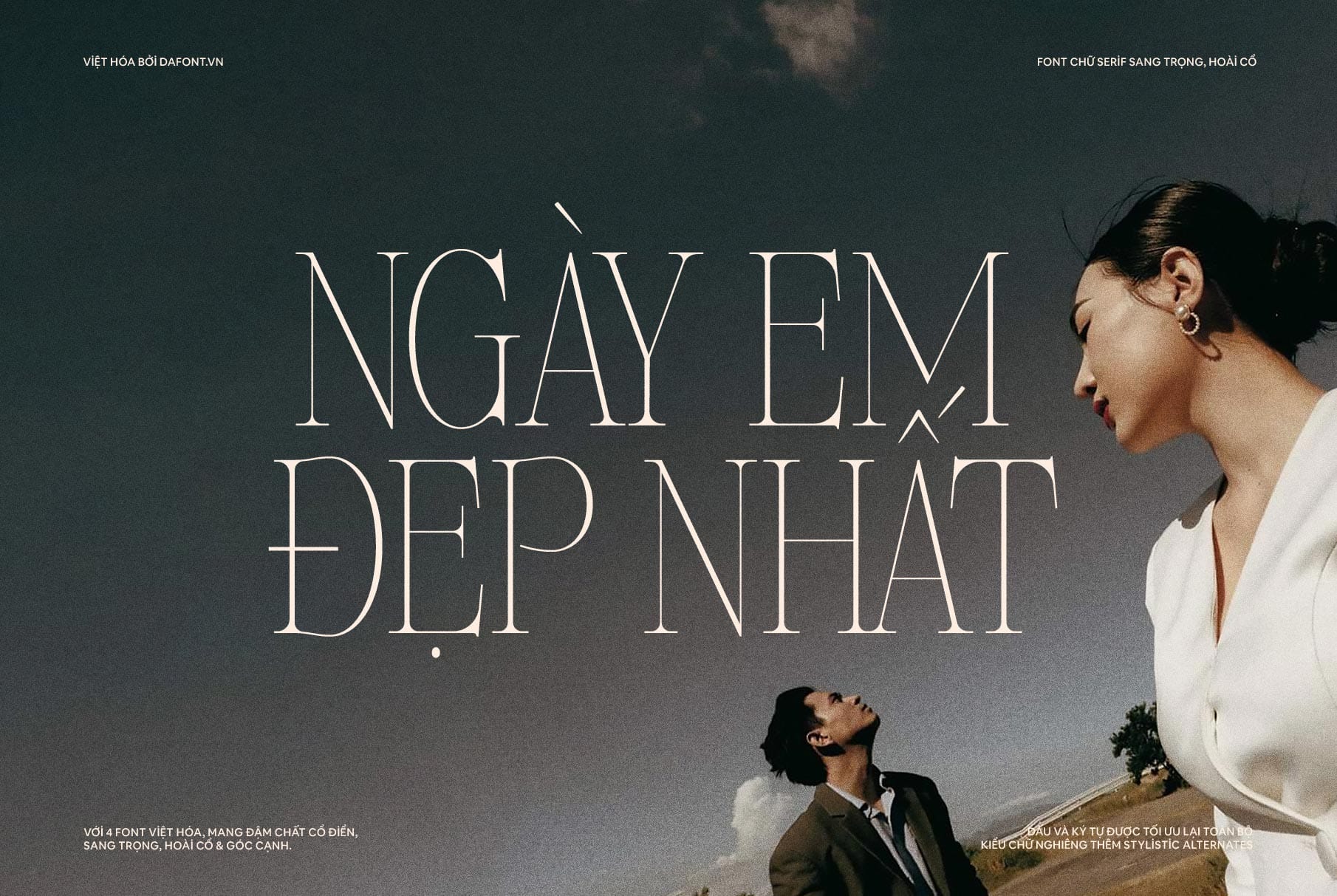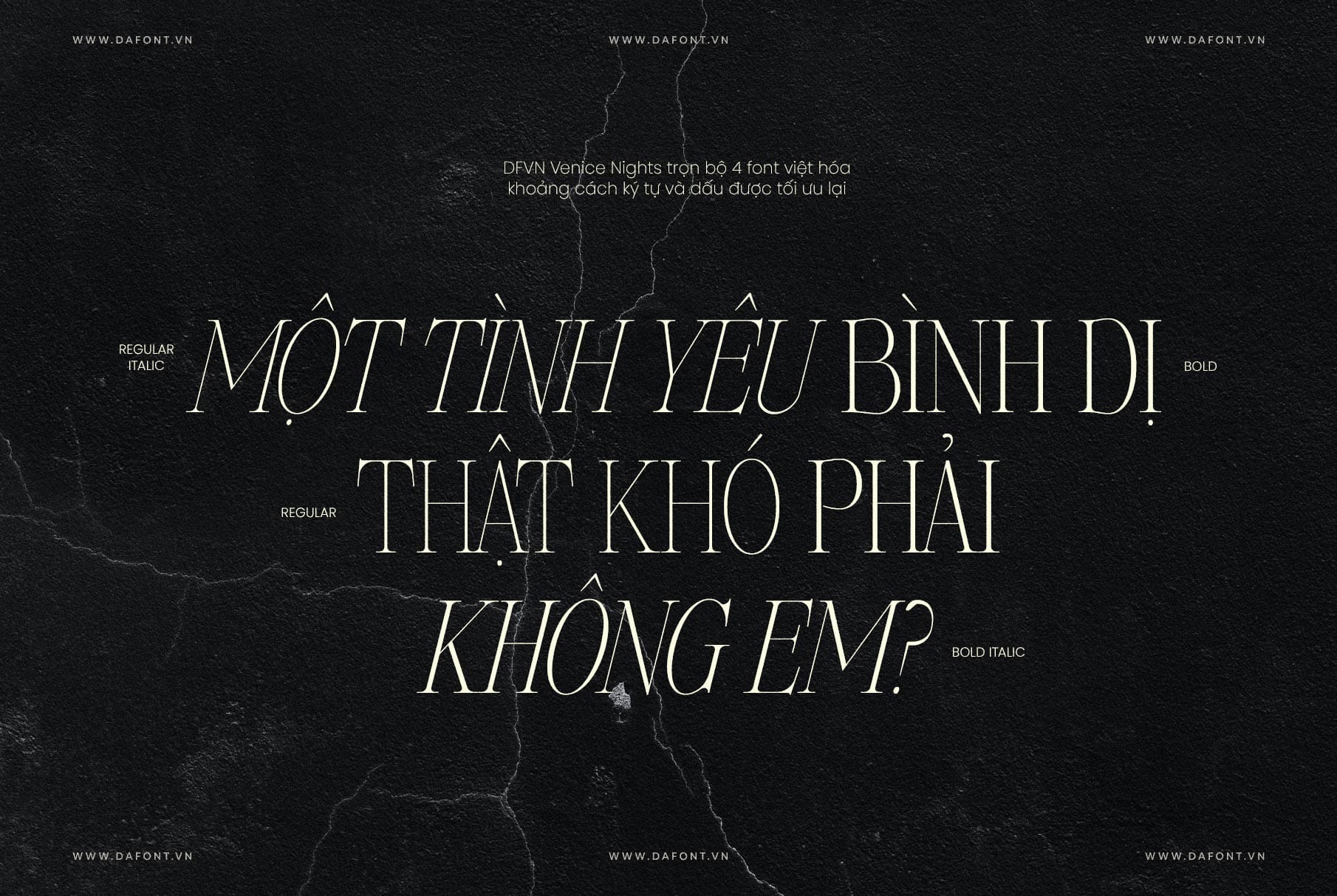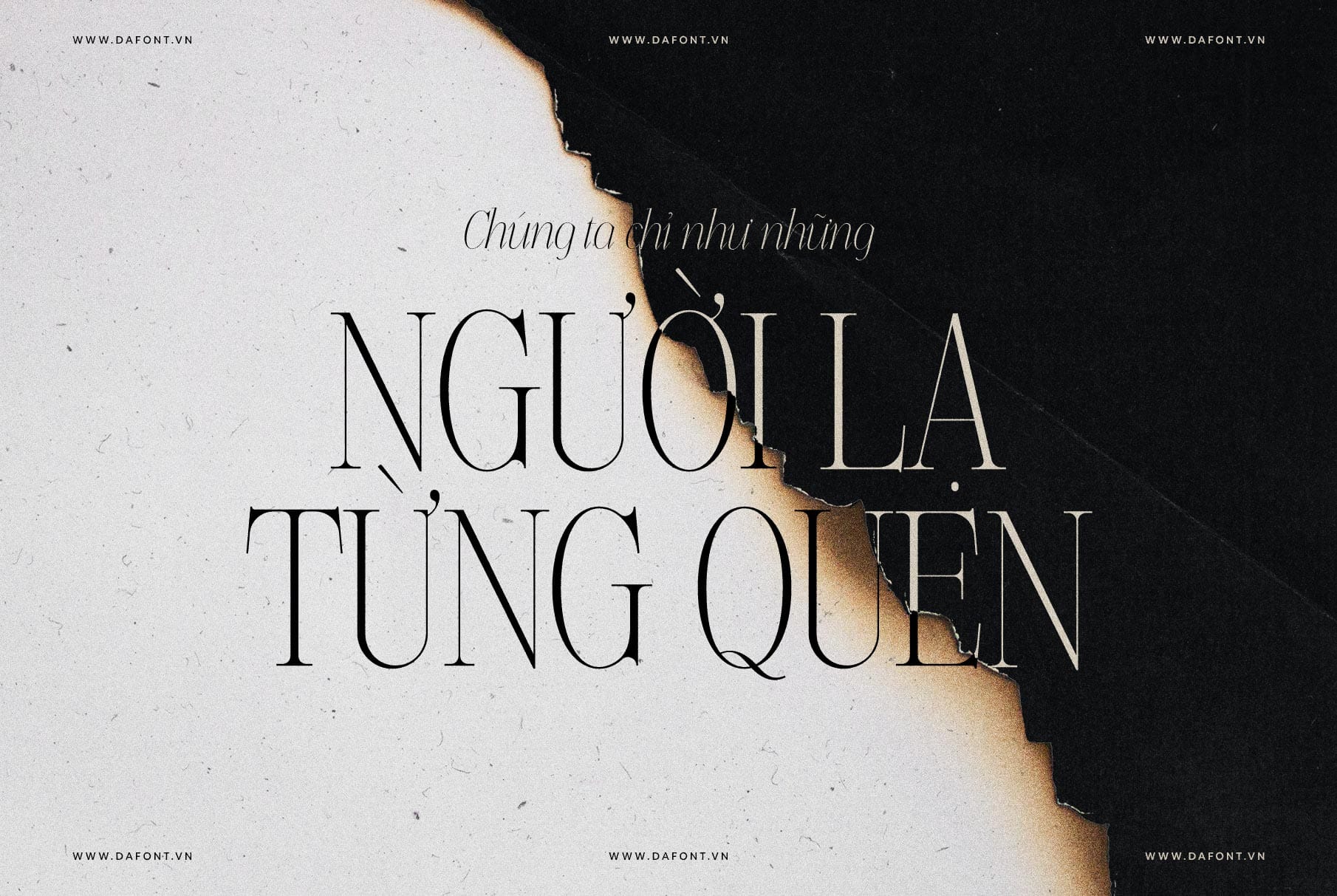
Bạn đang tìm kiếm một font chữ độc đáo, mang đậm hơi thở cổ điển nhưng vẫn toát lên vẻ đẹp hiện đại và tinh tế? DFVN Venice Nights chính là sự lựa chọn hoàn hảo dành cho bạn! Với sự kết hợp độc đáo giữa nét cổ điển và hiện đại, font serif này sẽ mang đến sự sang trọng và ấn tượng cho mọi thiết kế của bạn.
DFVN Venice Nights – Sự kết hợp giữa cổ điển và hiện đại
Venice Nights không chỉ là một font chữ, đó là một tác phẩm nghệ thuật kết hợp hoàn hảo giữa phong cách vintage & chic, nostalgic & super elegant, curvy & angled. Lấy cảm hứng từ những đêm Venice lãng mạn, Venice Nights mang đến cảm giác hoài cổ, quý phái nhưng không kém phần hiện đại và tinh tế.
Điều gì khiến DFVN Venice Nights trở nên đặc biệt?
- Thiết kế độc đáo: Venice Nights sở hữu những đường cong mềm mại, uyển chuyển kết hợp cùng các góc cạnh sắc sảo, tạo nên một tổng thể hài hòa, thu hút mọi ánh nhìn.
- Đa dạng lựa chọn: Với 4 kiểu chữ Regular, Italic, Bold và Bold Italic, bạn có thể thỏa sức sáng tạo và biến hóa cho phù hợp với từng mục đích thiết kế.
- Ứng dụng linh hoạt: Venice Nights có thể “cân” tất mọi thiết kế. Từ logo, quote, poster, branding, website headline, newsletter… cho đến mạng xã hội.
- Hỗ trợ ngôn ngữ đa dạng: Venice Nights hỗ trợ đầy đủ các ký tự, dấu câu, chữ số và dễ dàng sử dụng ligatures trên nhiều nền tảng, kể cả Canva.
Font Venice Nights là một sự lựa chọn hoàn hảo dành cho các nhà thiết kế muốn tạo ra những tác phẩm thiết kế ấn tượng và tinh tế. Với thiết kế độc đáo, phong cách hoài cổ nhưng vẫn mang những nét hiện đại, font này sẽ giúp bạn tạo ra những tác phẩm thiết kế sang trọng và thu hút.
DFVN Venice Nights đã được Việt hóa đầy đủ và tinh chỉnh lại kerning cho toàn bộ các ký tự. Các kiểu chữ nghiêng còn được bổ sung thêm các stylistic alternates, giúp bạn dễ dàng thay đổi một số ký tự thay thế thông qua tính năng Opentype, mang lại trải nghiệm sử dụng phong phú hơn.